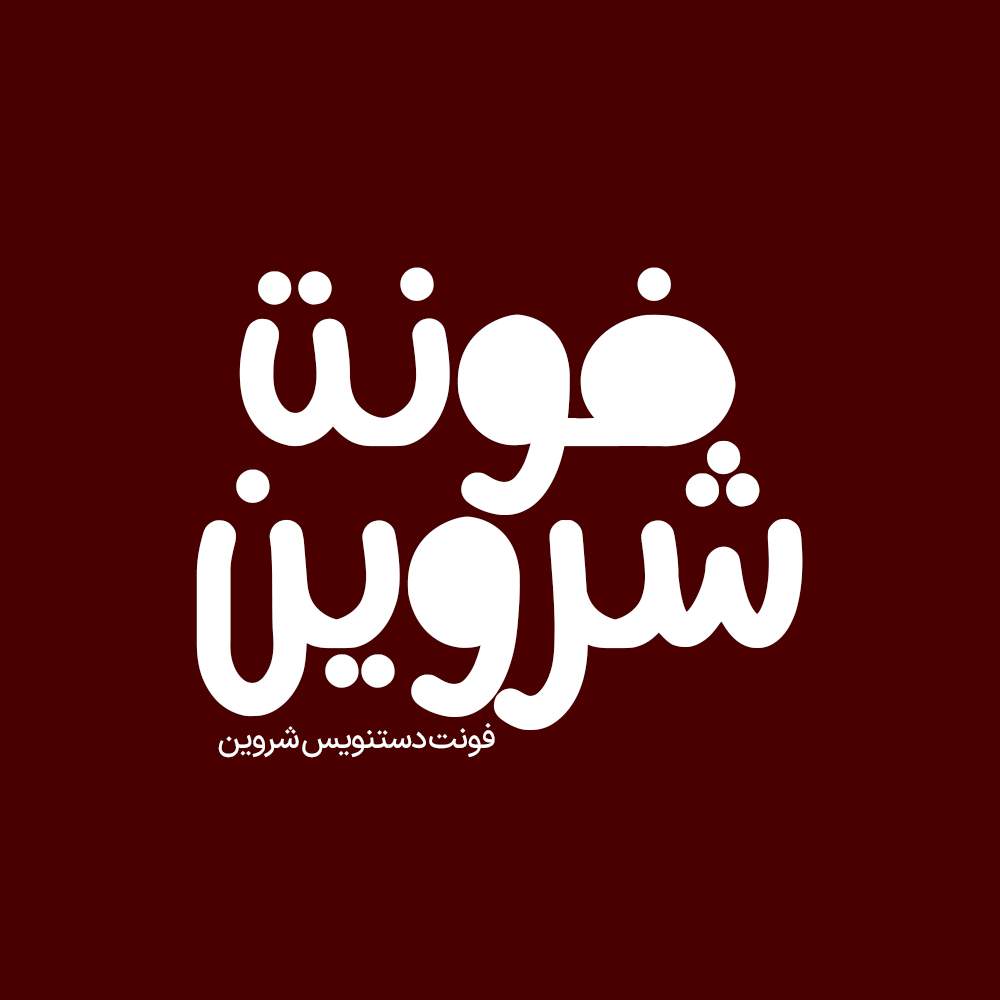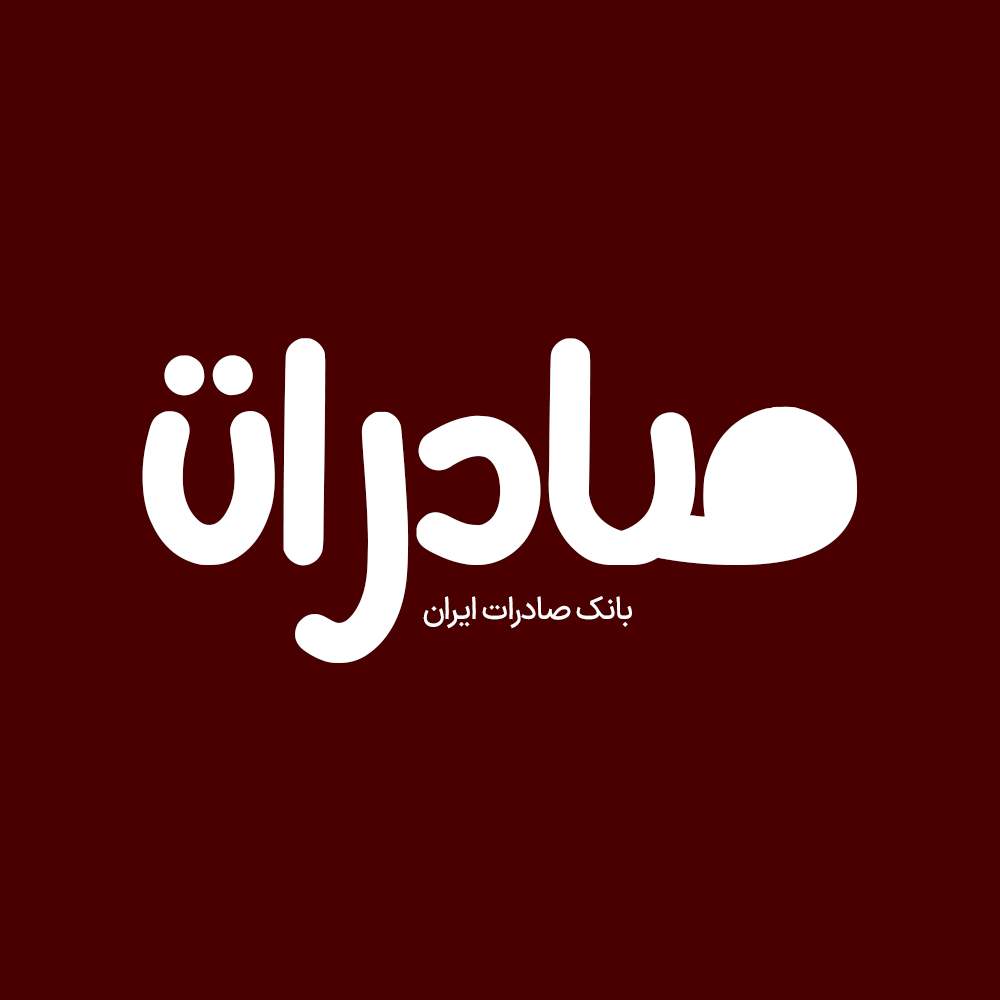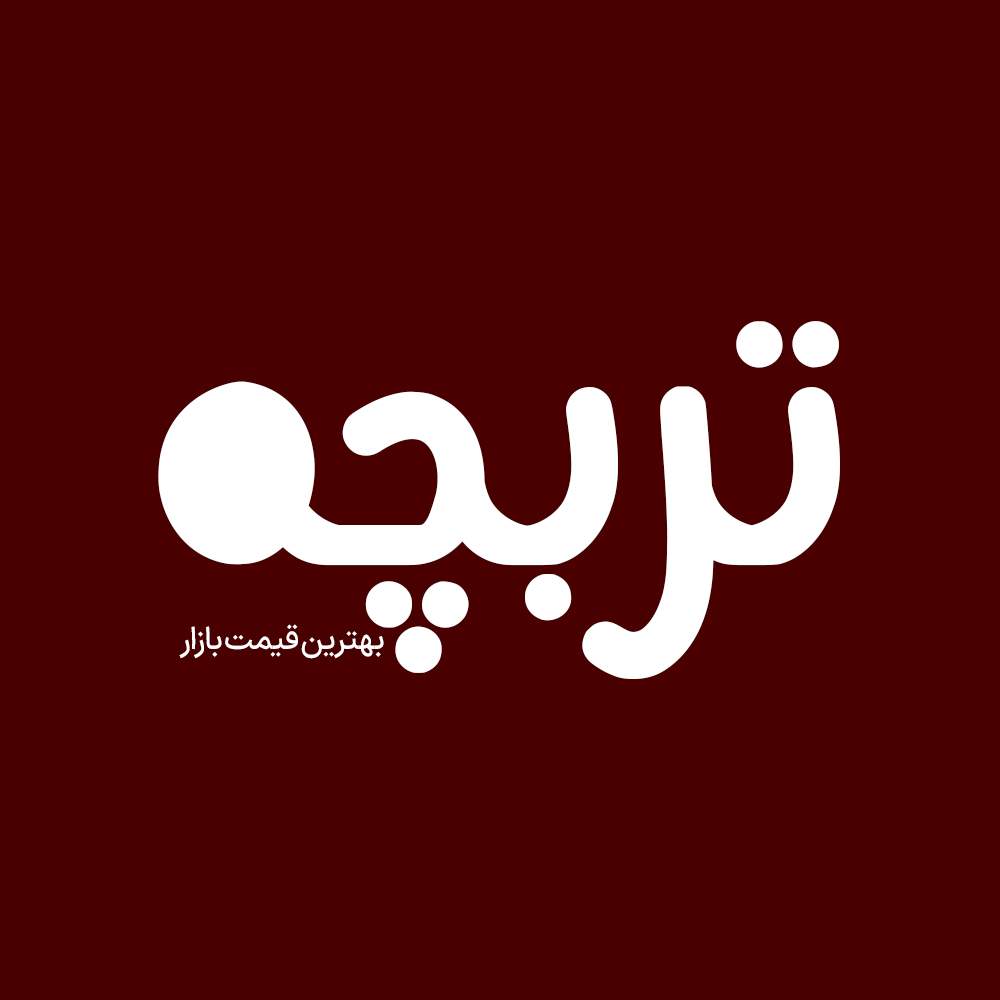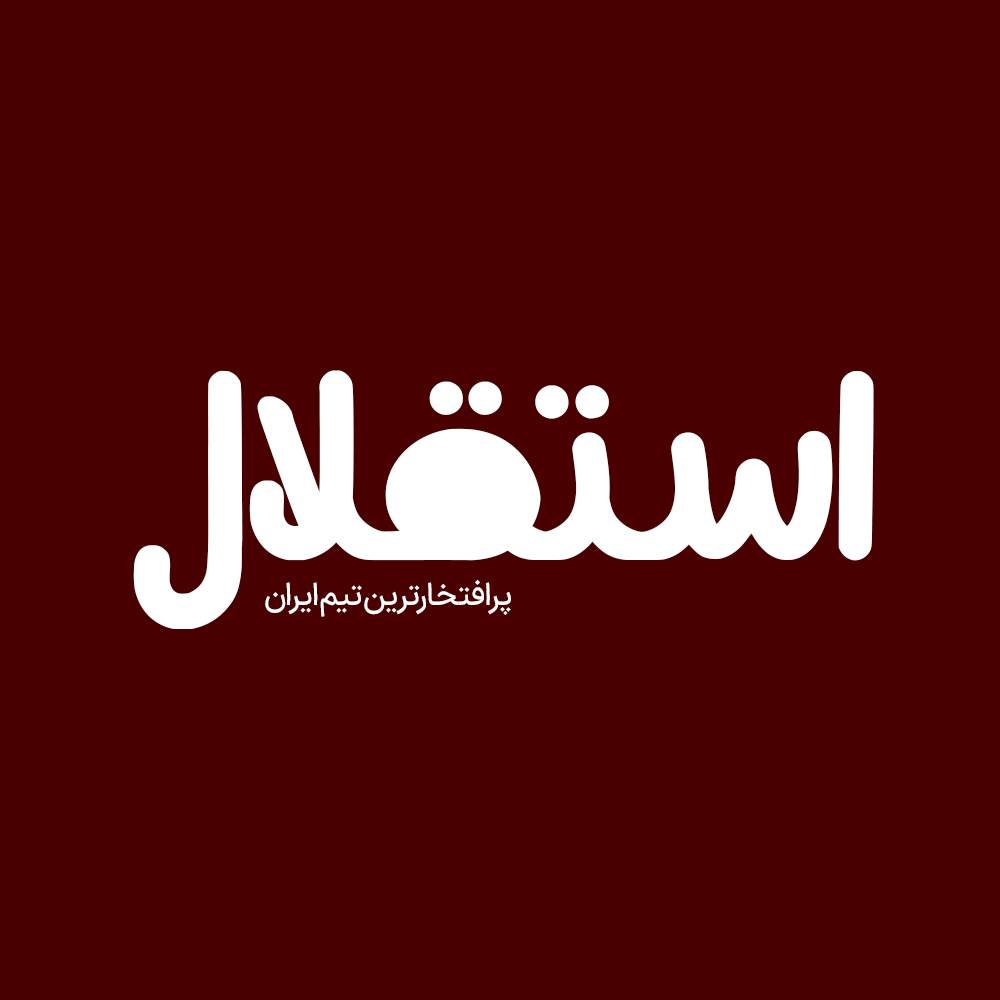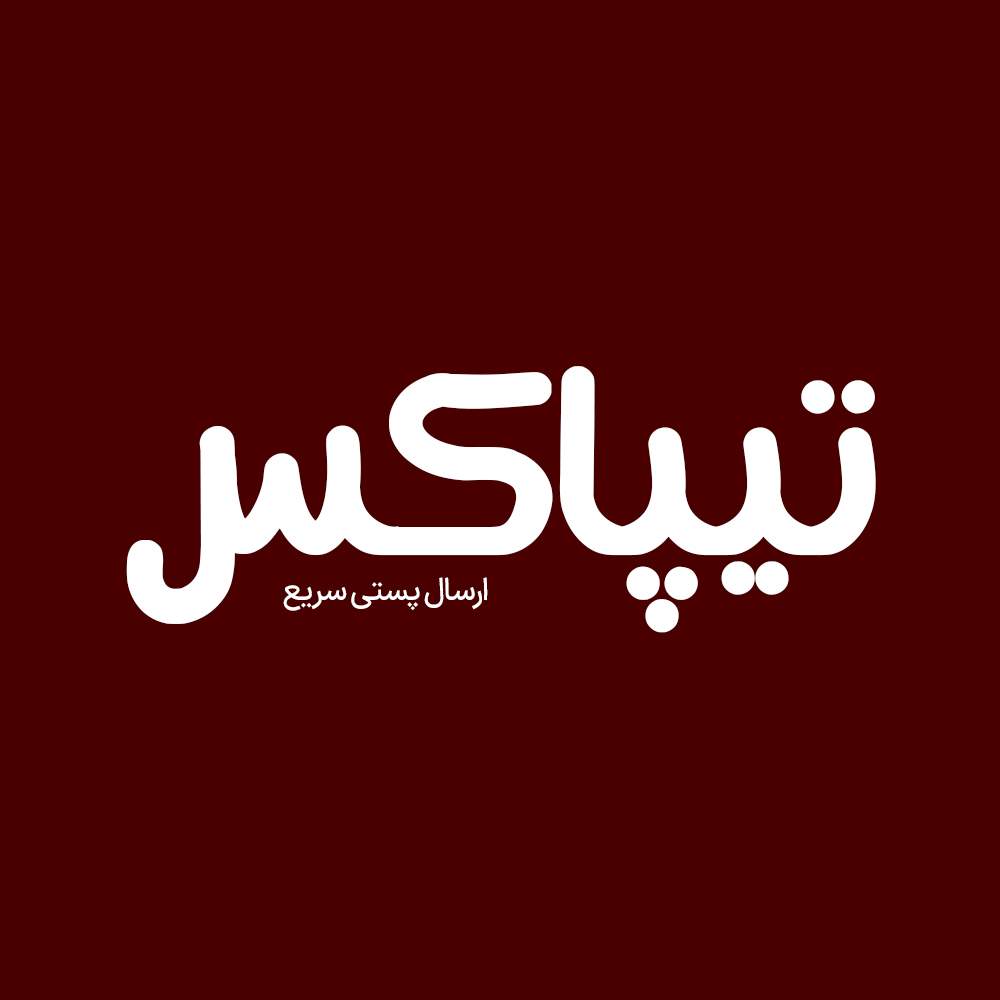
فونت فارسی شروین Shervin Font
فونت فارسی شروین یکی از متفاوتترین و چشمگیرترین فونتهای نمایشی فارسی است که به طور ویژه برای طراحی پوسترهای تبلیغاتی، کاورهای حرفهای، لوگوتایپهای خلاق و طرحهای…
فونت فارسی شروین یکی از متفاوتترین و چشمگیرترین فونتهای نمایشی فارسی است که به طور ویژه برای طراحی پوسترهای تبلیغاتی، کاورهای حرفهای، لوگوتایپهای خلاق و طرحهای گرافیکی قدرتمند ساخته شده است. فونت زیبای شروین با یک ساختار هندسی خاص توانسته به انتخاب اصلی طراحانی که قصد دارند طراحی متفاوت، خاص و کاملا متمایز ارائه دهند شود.
پیشنمایش و نمونه تایپ های فونت شروین